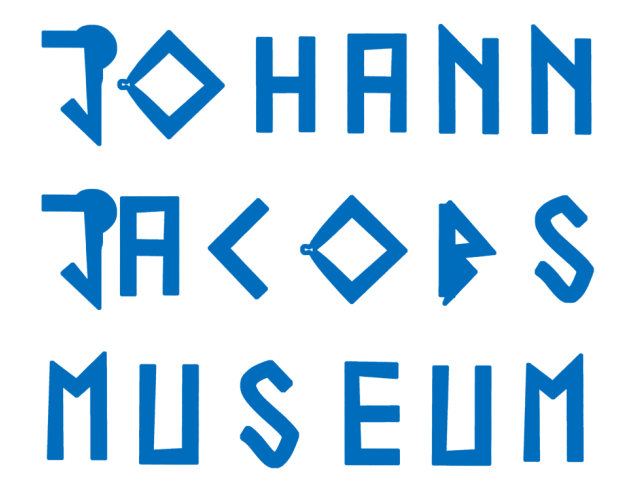
Johann Jacobs Museum: neues Erscheinungsbild
Im dt polarisiert es die noch zögerliche Diskussion und da es um eine typografielastige Gestaltung geht, erlaubt ich mir, das Thema auch hier aufs Tapet zu bringen. Im Kern der Diskussion im dt steht die Frage: Ist das Kunst oder Kommunikationsdesign? Und wie wäre das im jeweiligen Fall zu bewerten? Was sagen die Typografen, was die Gestalter?
Mal ganz ohne den theoretischen Hintergrund, den das Ganze haben mag: Auf mich wirkt die Gestaltung, wenn ich sie ganz unvoreingenommen betrachte, unfertig und irgendwie lieblos. Und in den unregelmäßigen Abständen zwischen den Buchstaben vermag ich keinen Sinn zu entdecken. Die meisten Menschen, die das neue Erscheinungsbild zu Gesicht bekommen, werden zuvor nicht mit Hintergrundwissen dazu versorgt worden sein. Ich frage mich, ob das Erscheinungsbild dann die Neugierde weckt oder ob es die Betrachter eher abstößt im Sinne von »Ich verstehe das nicht, es schüchtert mich ein, ist wohl nicht für mich gemacht.«
Kommunikationsdesign hat ja die Aufgabe, Menschen einzubeziehen, ihnen Dinge zu erklären und sie anzuregen, an etwas teilzunehmen. Ich habe meine Zweifel, ob das mit dieser Gestaltung so ohne weiteres gelingen wird. Da muss sicherlich eine ganze Menge an Öffentlichkeitsarbeit geleistet werden. Spontan erinnert mich die Gestaltung an die experimentellen Ansätze, mit denen sich so manches Theater in der Vergangenheit verhoben hat.
Kunst hingegen hat die Eigenschaft, sich auch mal nicht augenblicklich zu erklären, sie möchte erschlossen werden von demjenigen, der sich mit ihr befasst. Oftmals gilt, dass man nur sehen kann, was man weiß. Das finde ich auch in Ordnung, ich frage mich nur, ob man so weit gehen sollte, schon bei der äußeren Erscheinung eines Museums auf dieses Konzept zu setzen …
Lohnt sich nicht wirklich drüber zu diskutieren wie ich finde. Soll wohl »experimentell« wirken, ist aber einfach nur hingekritzelt. Erinnert im Ansatz ein wenig an David Carson, ist wohl nur ein Versuch eine angestaubte Branche auf schicke Mode Boutique zu trimmen. Kann man machen, wenn man kein Konzept hat, die Agentur dahinter macht aber scheinbar nichts anderes.
nach dem die ganzen partyflyer und studenten arbeiten in den letzten zwei jahren so aussahen, hat es auch mal eine institution erreicht.
das bauahaus in dessau hat auch schon sachen in der richtung rausgehauen.
um jeden preis anders, hässlich als cool?
ich kann damit auch nicht viel anfangen, ein trend der hoffentlich bald vorbei ist.
Wenn es wenigstens ordentlich gemacht wäre ... aber das ist sowas von Masche (um nicht zu sagen »Abzocke«, weil bestimmt nicht billig bei all dem »Anspruch«), was die Agentur hier veranstaltet, das langweilt einfach bloß.
Da ich vor Jahren mal selbst eine kurze Weile in einem Museum arbeiten durfte, kann ich mir vorstellen, wie sehr auch hier wieder von so einem Direktor-Kurator-Impressario-Intendanten um »Identität« gerungen wurde. Aber sorry, wenn ich Besucher ins Haus holen will, dann muss ich draußen erstmal kommunizieren. Kunst gibt's dann notfalls drinnen.
Nachtrag: Das hoffe ich auch, dass hässlicher Dilettantismus kein Trend wird ...
Mal rein von der typografischen Seite betrachtet: Wenn man so eine rustikale Kartoffeldruckschrift zum Gestaltungskonzept erheben will – das kann man ja durchaus machen – dann verstehe ich nicht, warum man bei den paar Buchstaben keine individuellen Formen für alle Zeichen entwirft, sondern alle gleichen Buchstaben gleich aussehen lässt. Nicht mal unterschiedlicher Farbauftrag oder leicht gedrehte Formen, Quetsch- oder Schmierränder als Stilmittel – nichts! Das ist einfach lieb- und einfallslos. Und es ist schade um das verschenkte Potenzial, welches die Idee ja durchaus gehabt haben könnte.
Guck dir mal die Seite von Vier5 an, dann denkst du eh nicht mehr über Potenzial nach.
Die arbeiten offensichtlich nach dem Motto: »Das muss so sch...e, sonst wär’s ja keine Kunst«.
Und dann erstmal ’ne ordentliche Rechnung stellen.
Da fragt man sich zwar zunächst, wer die eigentlich beschäftigt, aber dann sieht man: Das sind alles so planlose Kulturfuzzis mit narzisstischen Neigungen. So jemand bezahlt auch Unsummen für Jonathan Meese.
Ja, weil: Wenn’s teuer ist, ist es ganz bestimmt echte Kunst – da kann man nichts falsch machen!  ;-)
By the way: Was hat denn die Agentur für eine grauenhafte Website? Die ist ja genauso kommunikationsfeindlich gestaltet …  :-?
Vier5 sind über jeden Zweifel erhaben. Wer die Beiden für ein Projekt engagiert, wird eine Gestaltung bekommen, die ganz klar den Vier5-Stempel trägt. Ich finde das vollkommen legitim und bewundere die Agentur dafür, dass sie mit ihrem »Anti-Stil« so erfolgreich sind.
… die haben was von den Schneidern in »Des Kaisers neue Kleider«. Da kann man sie für ihre Dreistigkeit bewundern und für ihren Geschäftssinn. Für mehr aber auch nicht. Über jeden Zweifel erhaben ist im Übrigen nicht mal der Papst.
Vier5 sind über jeden Zweifel erhaben. Wer die Beiden für ein Projekt engagiert, wird eine Gestaltung bekommen, …
Das meinte ich weiter oben: Ich glaube, dass dieser Boutique-Eindruck bei den Betrachtern des Museums-CDs entstehen könnte und frage mich, ob das gewollt ist. Die meisten Museen haben doch eher den Ansatz, sich und ihr Angebot einer möglichst breiten Öffentlichkeit zugänglich zu machen. Ein Corporate Design, welches diese Tür von vornherein absichtlich nur zur Hälfte öffnet, muss sich doch fragen lassen, aus welchen Grund dies so ist.